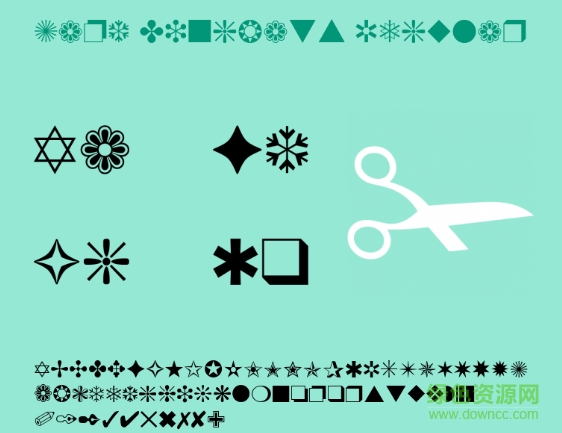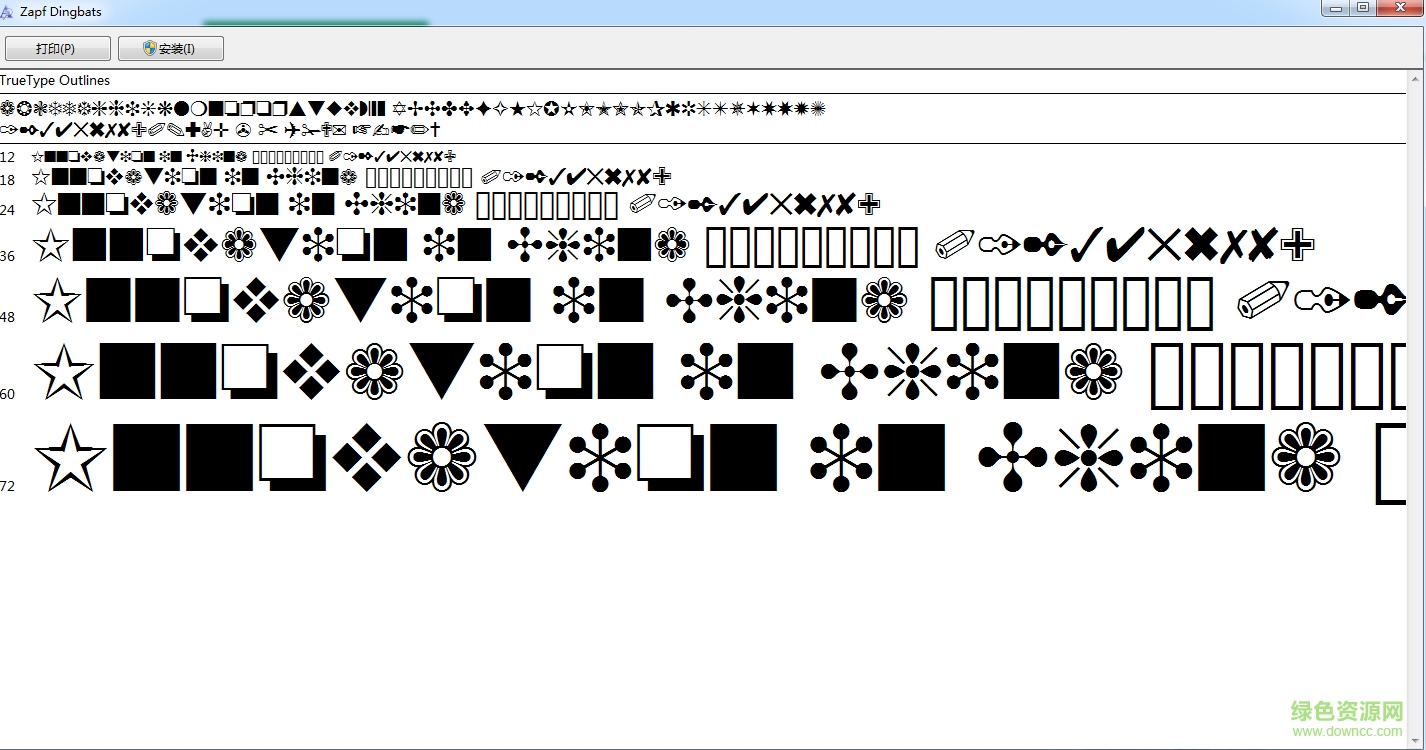
zapfdingbatsitc
zapfdingbatsitc字體是一款特殊的符號(hào)字體,包含了三角形、正方形、對號(hào)、叉叉、雪花、十字架、五角星、菱形、花朵、鉛筆等一系列符號(hào),可用作廣告字體,歡迎大家在綠色資源網(wǎng)免費(fèi)下載!
zapfdingbatsitc字體